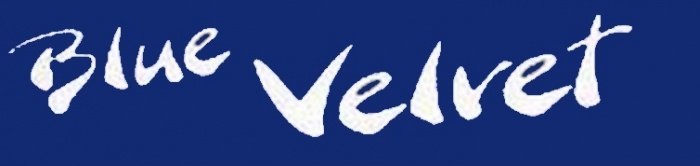
Schriftart von Visitenkarte
Hallo ich würde gerne wissen welche Schriftart, der folgende Schriftzug hatt?post-24050-0-09684200-1374416327_thumb.j
Hab ich von einer Visitenkarte eingescannt.
Das ist die Schriftart, die bei der unsäglichen Diddl-Maus eingesetzt wird. Die wird da ihren eigenen Font haben ... keine Ahnung, ob der zur freien Verfügung steht  :-?
So weit ich mich erinnere ist das eine frei verfügbare Schrift – entweder käuflich zu erwerben oder frei. Ich meine mich sogar zu erinnern, dass ich die irgendwo habe. Ich schaue mal kurz nach und wenn ich sie finde melde ich mich gleich wieder.  :-)
Rückmeldung: Ich habe mich getäuscht – meine Schrift ist nur so ähnlich. Wenn man das Thema aber mal googelt, erhält man zwischen diversen dubiosen Quellen einen ulkigen Beitrag im Fontblog zur Diddl-Schrift …